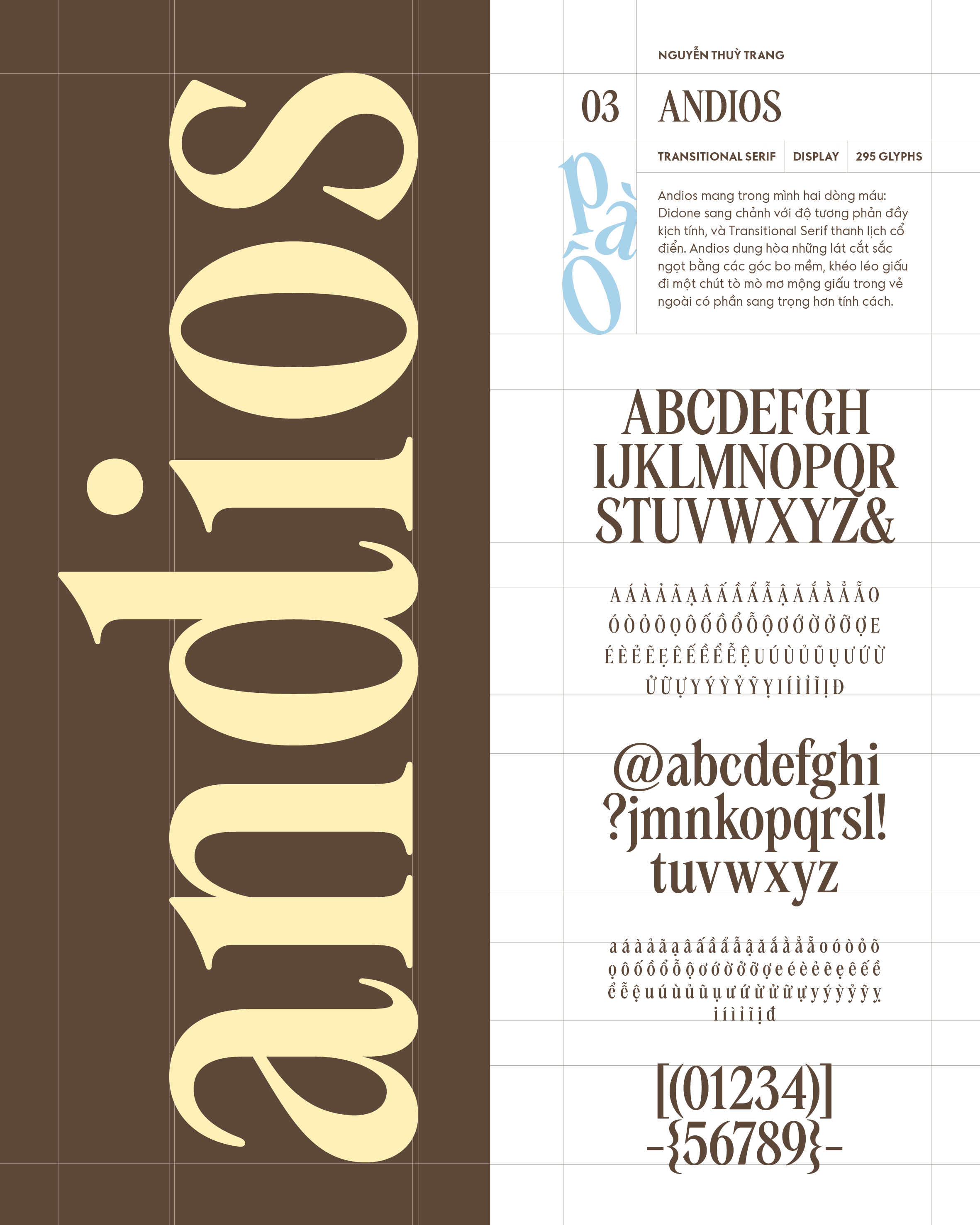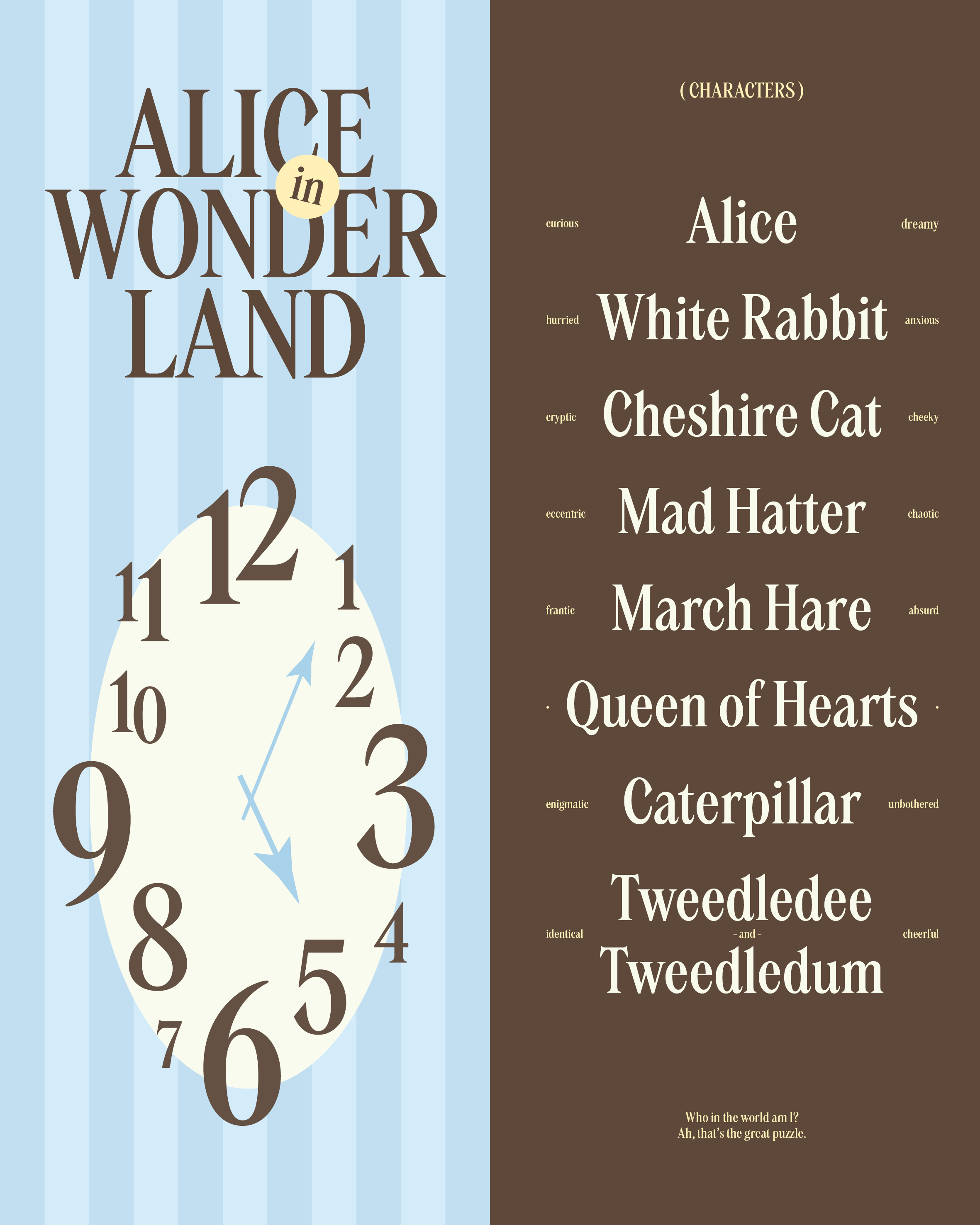
Andios
Về Andios: Andios mang trong mình hai dòng máu: Didone sang chảnh với độ tương phản đầy kịch tính, và Transitional Serif thanh lịch cổ điển. Andios dung hòa những lát cắt sắc ngọt bằng các góc bo mềm, khéo léo giấu đi một chút tò mò mơ mộng giấu trong vẻ ngoài có phần sang trọng hơn tính cách.
Transitional Serif
Display
Nguyễn Thùy Chang